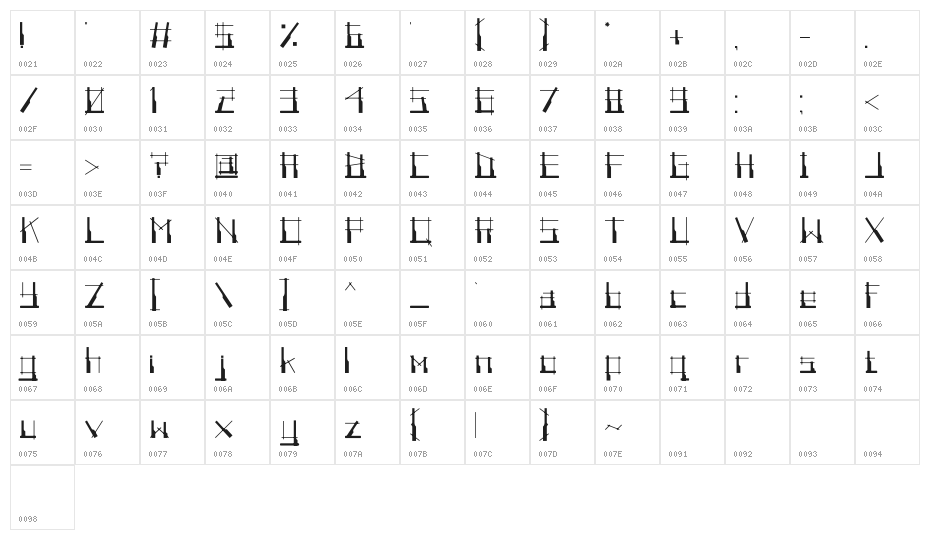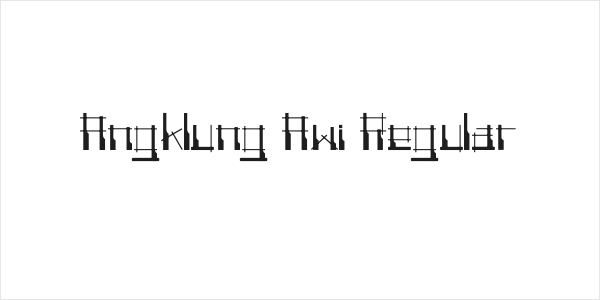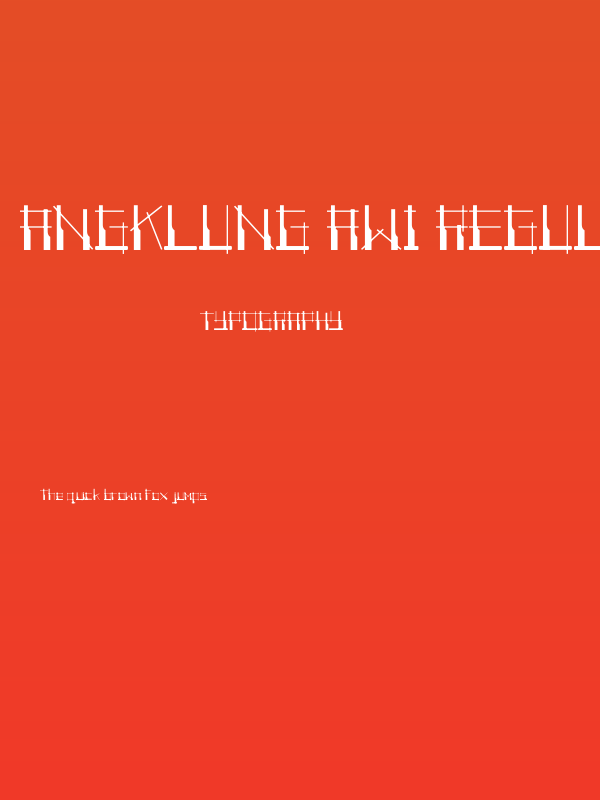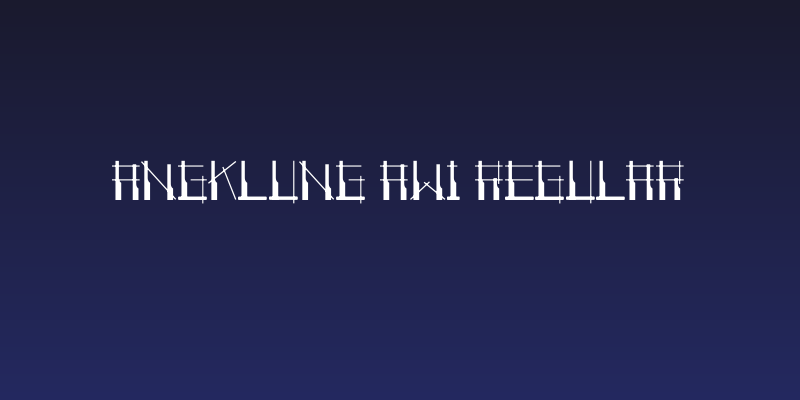
Angklung Awi Regular Font
| Caso de uso | Logos, Posters, Artistic projects |
| Projetos propostos | Ideal for cultural event posters, artistic projects, and unique branding materials. |